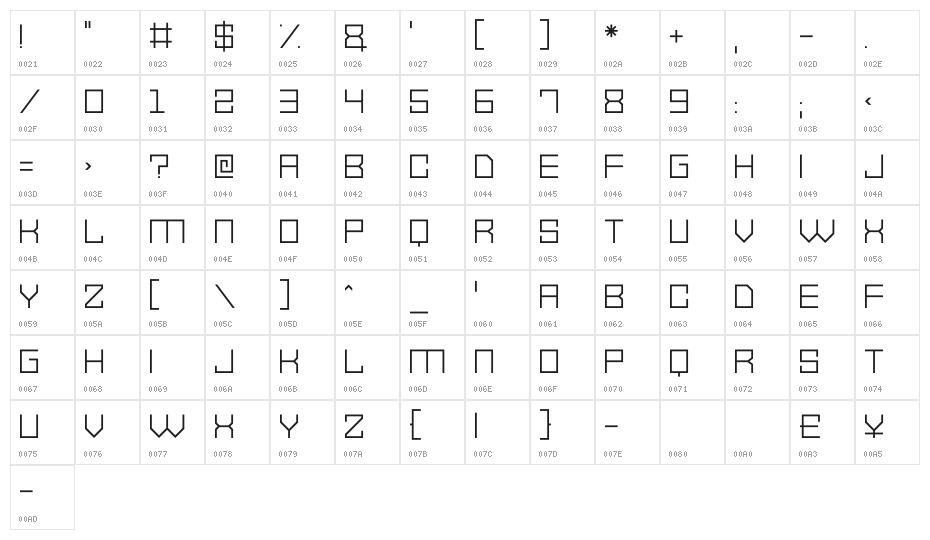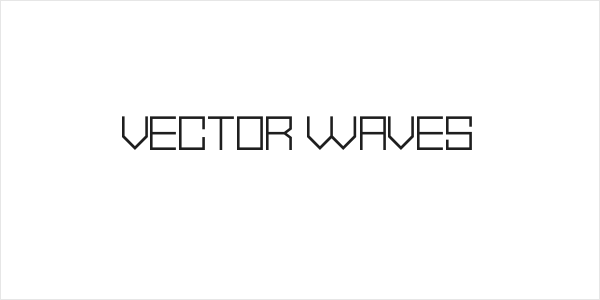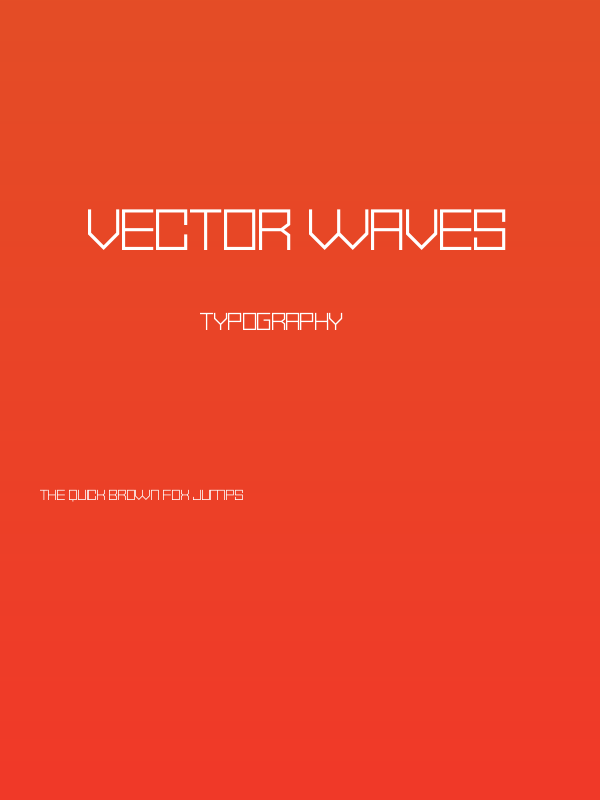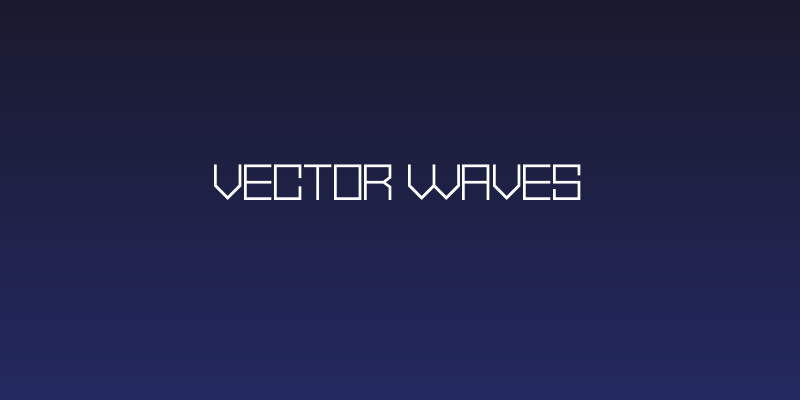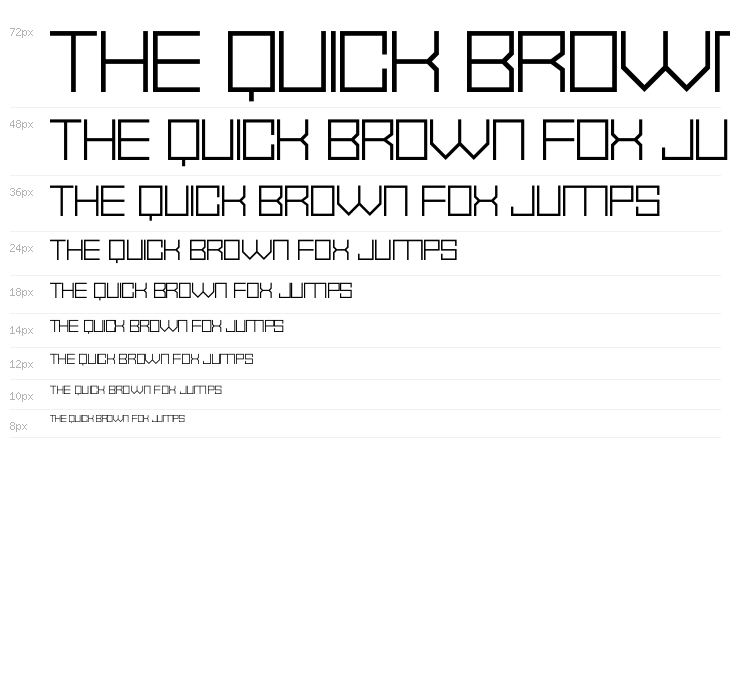
Vector Waves Font
| Caso d'uso | Headlines, Logos, Digital media |
| Progetti proposti | Ideal for technology-themed projects, branding, logos, and digital media that require a modern and futuristic touch. |